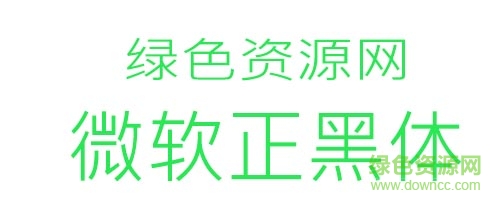
這個粗體不是單純將普通字符加粗,而是在具體筆畫上分別進(jìn)行處理,因此是獨(dú)立的一個字體。當(dāng)使用于不能顯示中文字型名稱的系統(tǒng)時,會顯示為Microsoft JhengHei,因此我們在選擇使用這款字體時要選擇Microsoft JhengHei。型依據(jù)的是臺灣“教育部”的國字標(biāo)準(zhǔn)字體的標(biāo)準(zhǔn)。隨Windows Vista及office 2007(繁體中文)一起發(fā)布,是Windows Vista缺省字體,在使用的ClearType功能的液晶顯示器中,其比以前Windows XP缺省的新細(xì)明體更加清晰易讀。